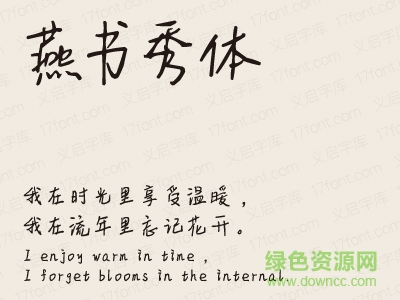
軟件介紹 軟件標簽: 義啟字體 字體 義啟燕書秀體字體是一款十分好看的義啟字體,線條柔和優(yōu)美,筆畫精致得當,整體看上去明朗流暢,有需要的朋友可以在綠色資源網(wǎng)免費下載收藏!義啟燕書秀體字體介紹義啟燕書秀體,是義啟字庫定制的第五款個人手寫體!義啟心花怒放字體安裝方法方法一:控制面板/字體/文件/安裝新字體;方法二:直接將字體復制到C:\WINDOWS\Fonts。方法三:針對win7系統(tǒng),用戶只需選中字體右鍵安裝即可。溫馨提示本站所有字體資源僅供個人學習與參考,如需商業(yè)使用請到相關官網(wǎng)授權! 軟件截圖 上一張下一張(1 / 1) 安裝詳細截圖 猜你喜歡 流行字體 義啟字體 流行字體 2017流行字體專題是小編為大家精心搜集整理的最新最火字體合集,包含了各式各樣的網(wǎng)絡流行字體,如流行手寫字體、時尚英文字體以及創(chuàng)意流行字體等! 查看更多>> 蘇新詩雙勾體字體 2.71M/中文/10.0/下載 時尚細黑簡體字體 6.28M/中文/10.0/下載 奇思娜娜體ttf 7.32M/中文/10.0/下載 三生三世十里桃花字體 6.27M/中文/4.0/ttf版下載 漢儀喵小姐體 811KB/中文/10.0/ttf版下載 暮夏何其孽字體 7.49M/中文/10.0/下載 義啟字體 義啟字體是義啟家族(17font)推出的一系列字體合集,包括了很多類型,如:義啟粗楷體ttf、義啟萌妹體、義啟明星字體等,每款字體都很有特點,當然,也很漂亮,很多朋友都喜歡使用義啟字體,趕快收藏起來吧! 查看更多>> 義啟風尚黑字體 842KB/中文/0.0/下載 義啟星空之翼ttf 782KB/中文/10.0/下載 義啟奶萌小小喵字體 1.31M/中文/0.0/ttf版下載 義啟戀上桃花拼音字體 1.29M/中文/5.0/ttf免費版下載 義啟小南同學字體 437KB/中文/5.0/ttf免費版下載 義啟為你心動字體 592KB/中文/6.6/ttf免費版下載 其他版本下載 標題 大小 更新日期 下載 下載地址 電腦版 義啟燕書秀體 點擊報錯 軟件無法下載或下載后無法使用,請點擊報錯,謝謝! 關閉報錯反饋 請描述您所遇到的錯誤,我們將盡快予以修正,謝謝! *必填項,請輸入內(nèi)容 本類最新 dreamweaver字體庫 首爾南山體字體 v1.06 官方版 潮字社風云簡ttf 潮字社凌渡鯤鵬簡體字體 潮字社曾玉波手書簡字體 微博慧心字體 相關文章 Photoshop字體安裝使用方法和技巧 如何解決“無法新增字體”問題 Win 7系統(tǒng)安裝字體方法 網(wǎng)頁字體大小設置方法 怎么改網(wǎng)頁字體大小 在Linux系統(tǒng)中安裝字體的幾種方法 windows7字體顯示問題:打開某些程序的時候顯示的是亂碼 用戶評論 熱門評論 最新評論 第 1 樓 四川綿陽鐵通客人 發(fā)表于: 2017/03/12 18:48:25 義啟燕書秀體很有韻味,結構勻稱,精致流暢,清秀得體,作海報設計再好不過了! 支持(0) 蓋樓(回復) 發(fā)表評論 查看所有評論(1) 昵稱: 請不要評論無意義或臟話,我們所有評論會有人工審核. 字數(shù): 0/500 (您的評論需要經(jīng)過審核才能顯示)